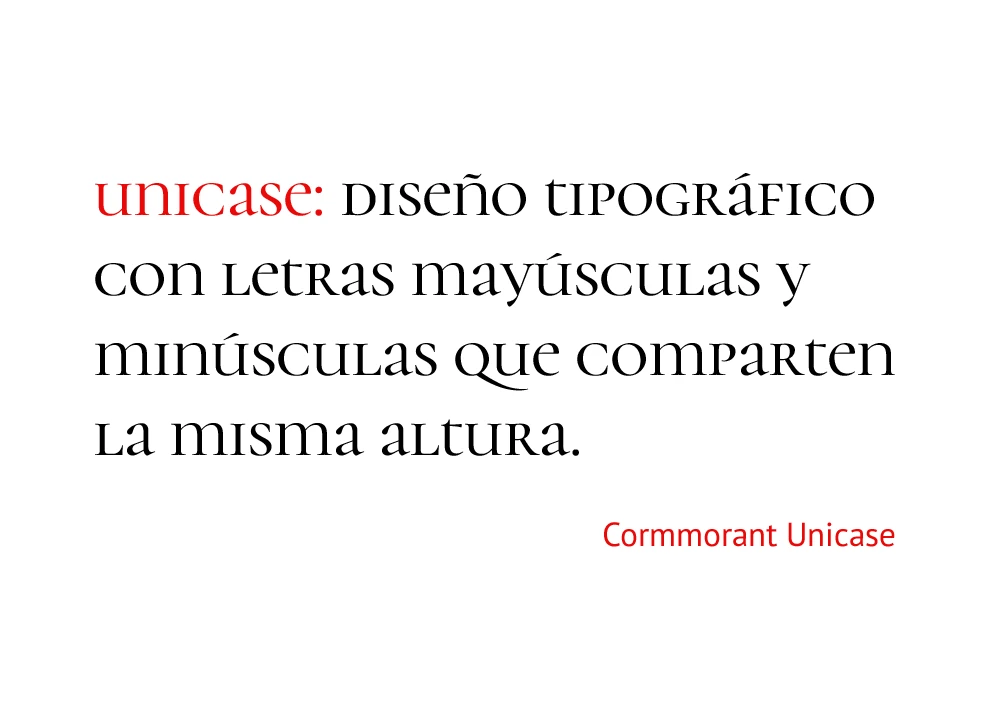
UNICASE
TIPOGRAFÍA. Es un término en inglés que designa a un diseño tipográfico de caja única, es decir uno que no distingue entre mayúsculas y minúsculas presentando una sola forma para cada letra.
LINGÜÍSTICA. Es un sistema de escritura o alfabeto unicameral. El persa, el kanarés, el tamil, el árabe, el hebreo, el georgiano y el coreano se escriben con alfabetos unicamerales, mientras que el latín moderno, el griego, el cirílico y el armenio son escritura de dos cajas o bicamerales.
Algunos especialistas suponen que todos los alfabetos de dos cajas fueron primero monocamerales. El latín, por ejemplo, se escribía como alfabeto de una sola caja en la época del Imperio romano, alfabeto que corresponde más o menos a la caja alta del alfabeto latino actual; posteriormente los escribas desarrollaron nuevos juegos de símbolos para el resto de los textos, que se han convertido en la caja baja del alfabeto latino.